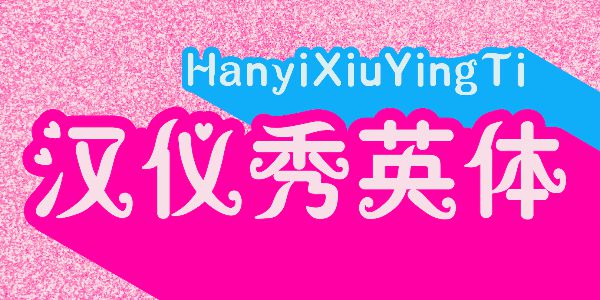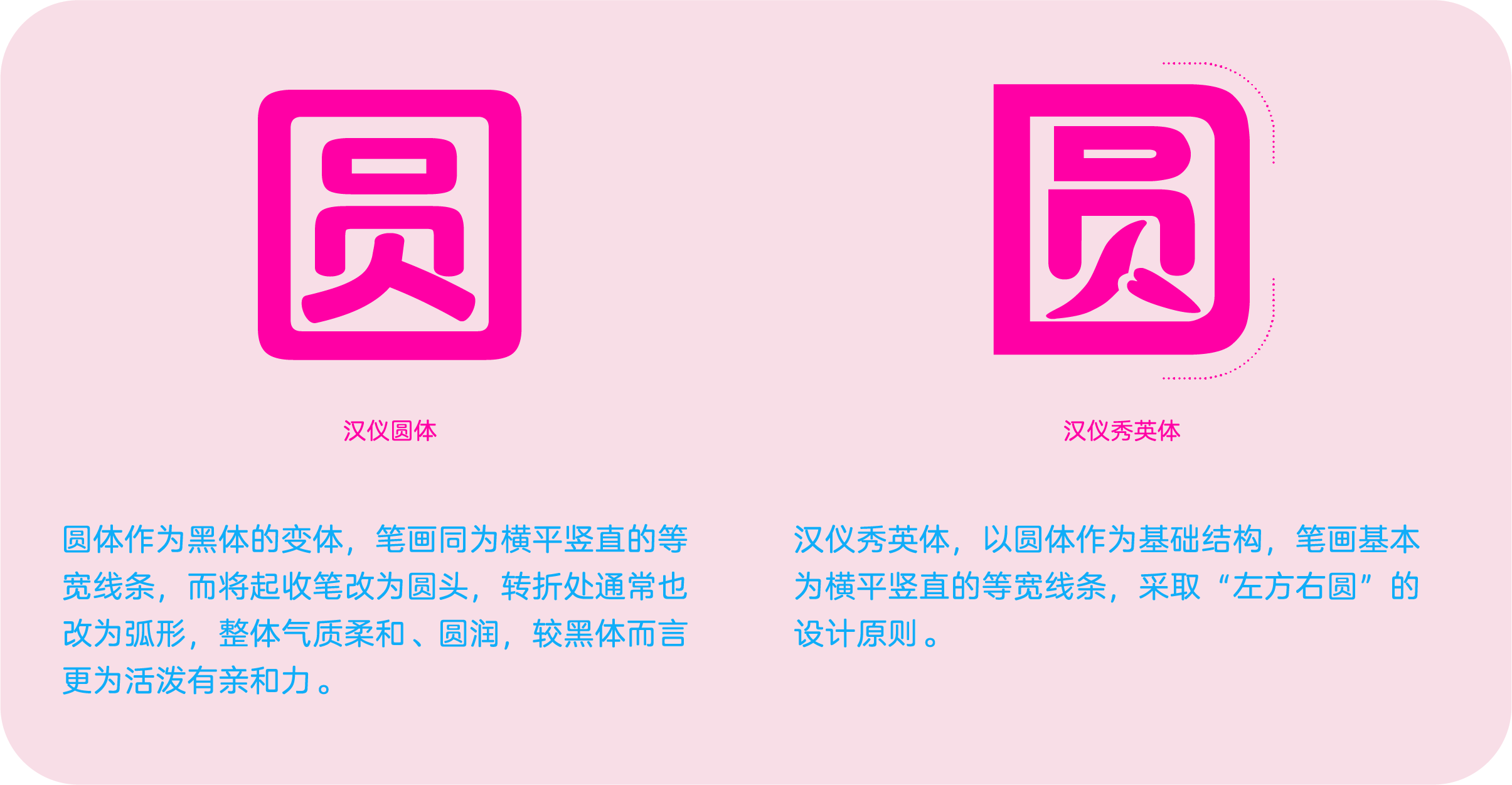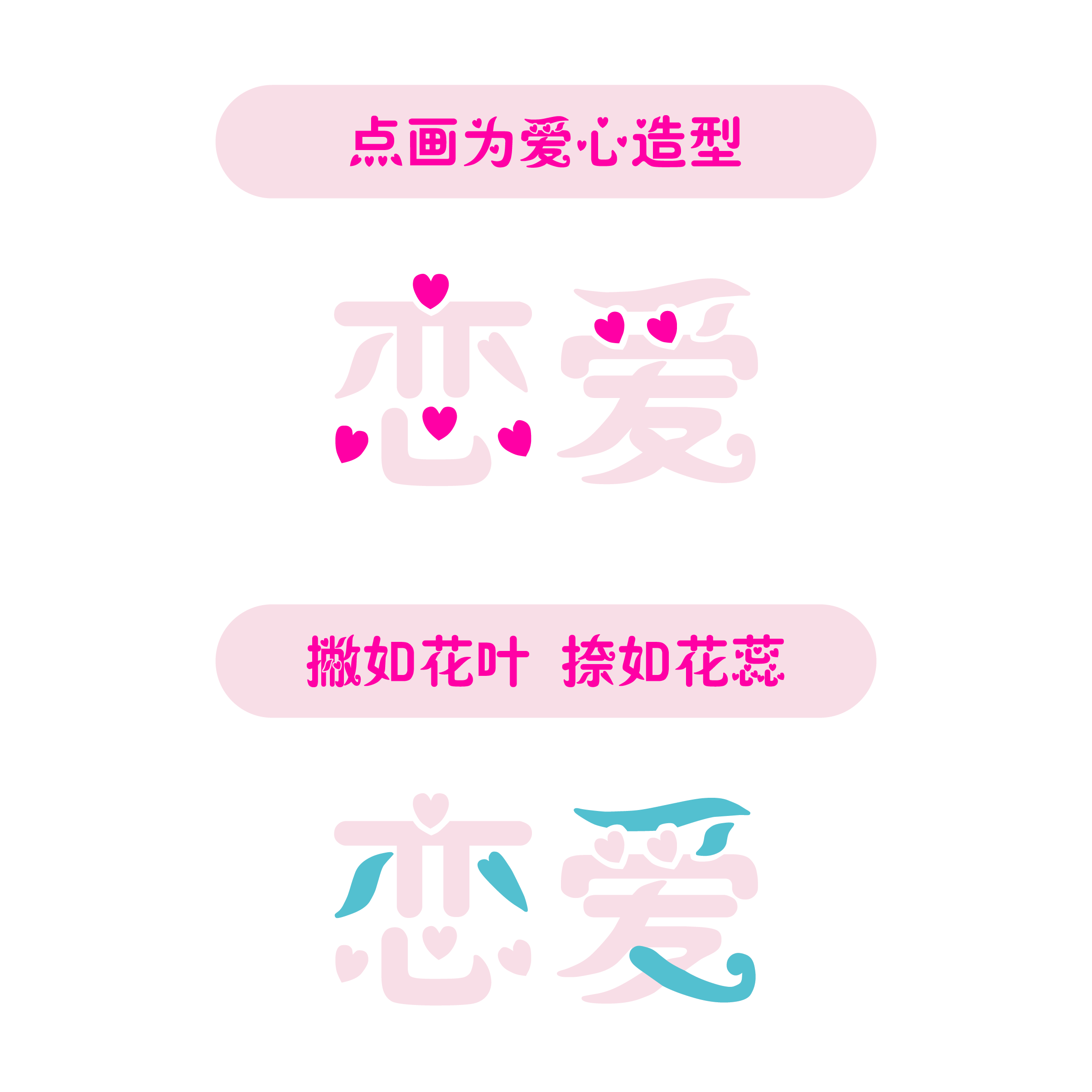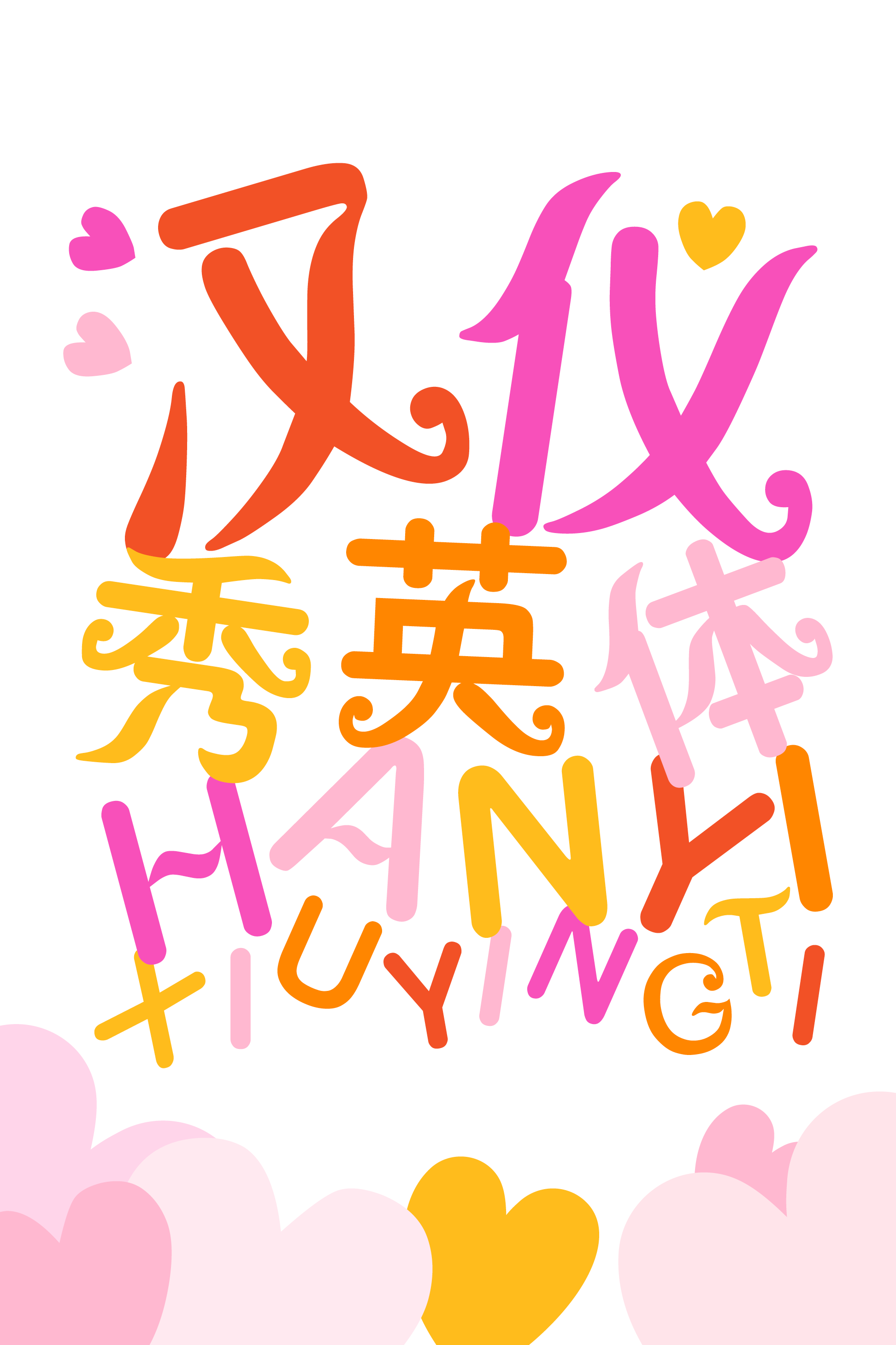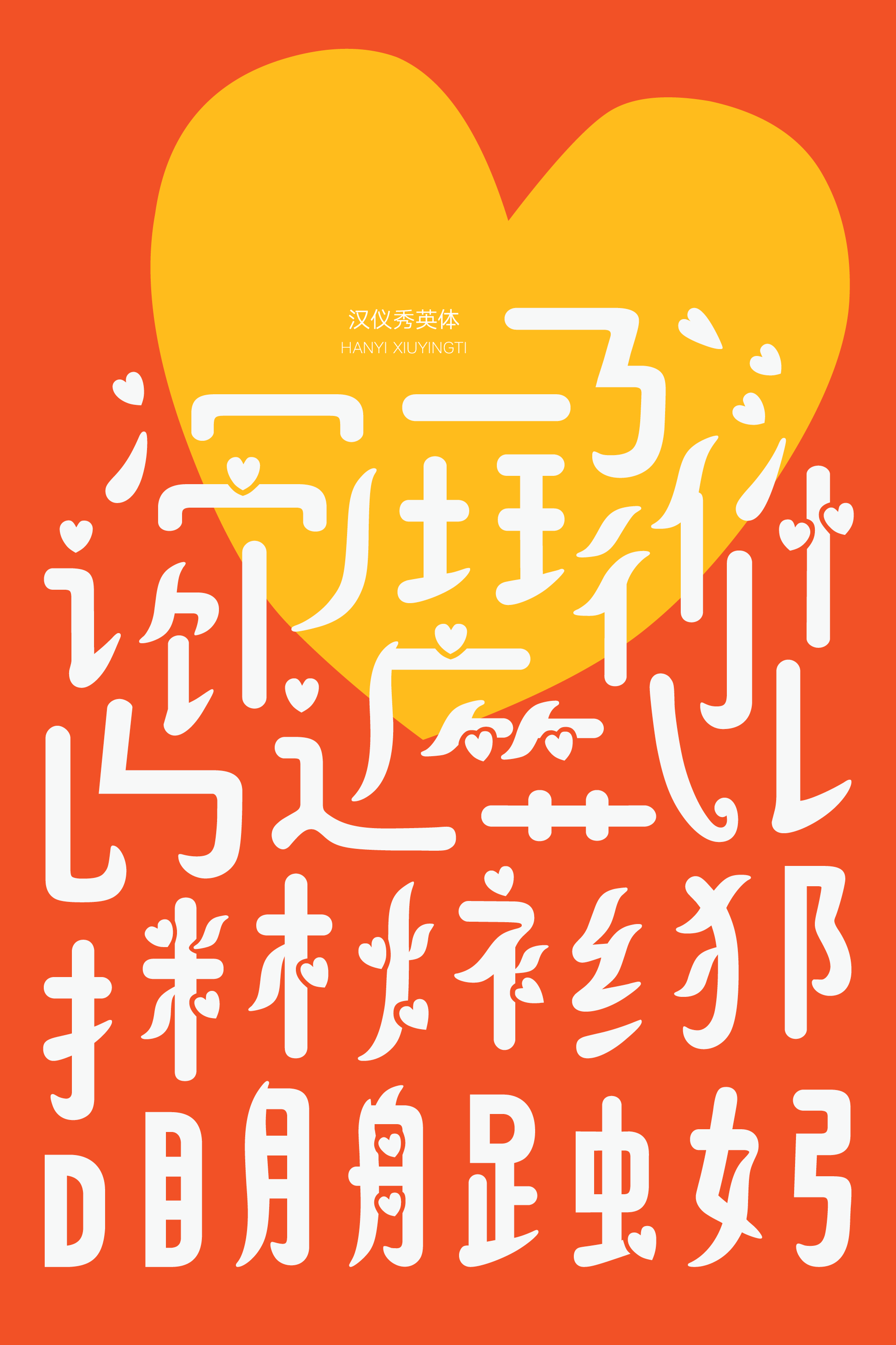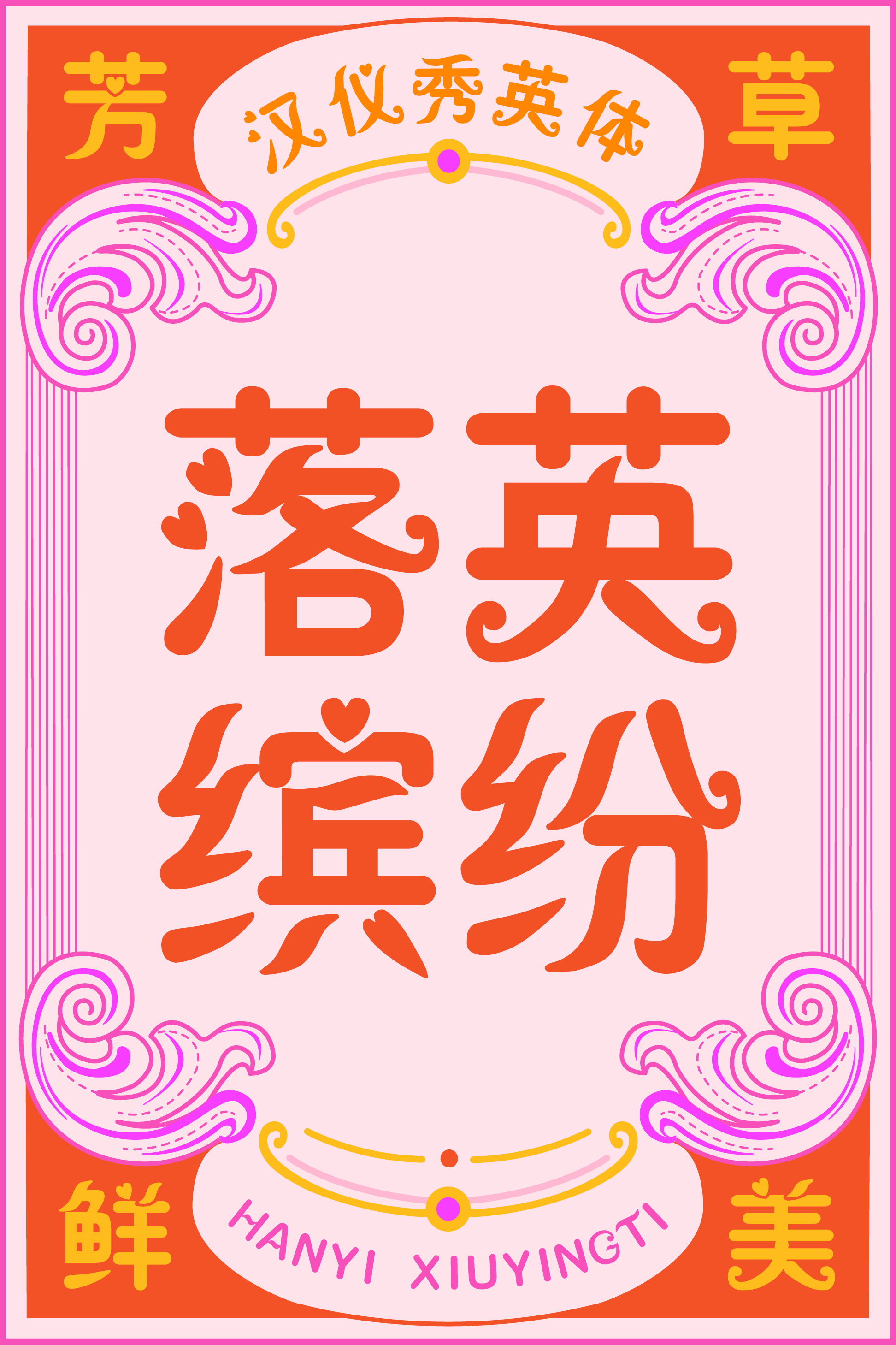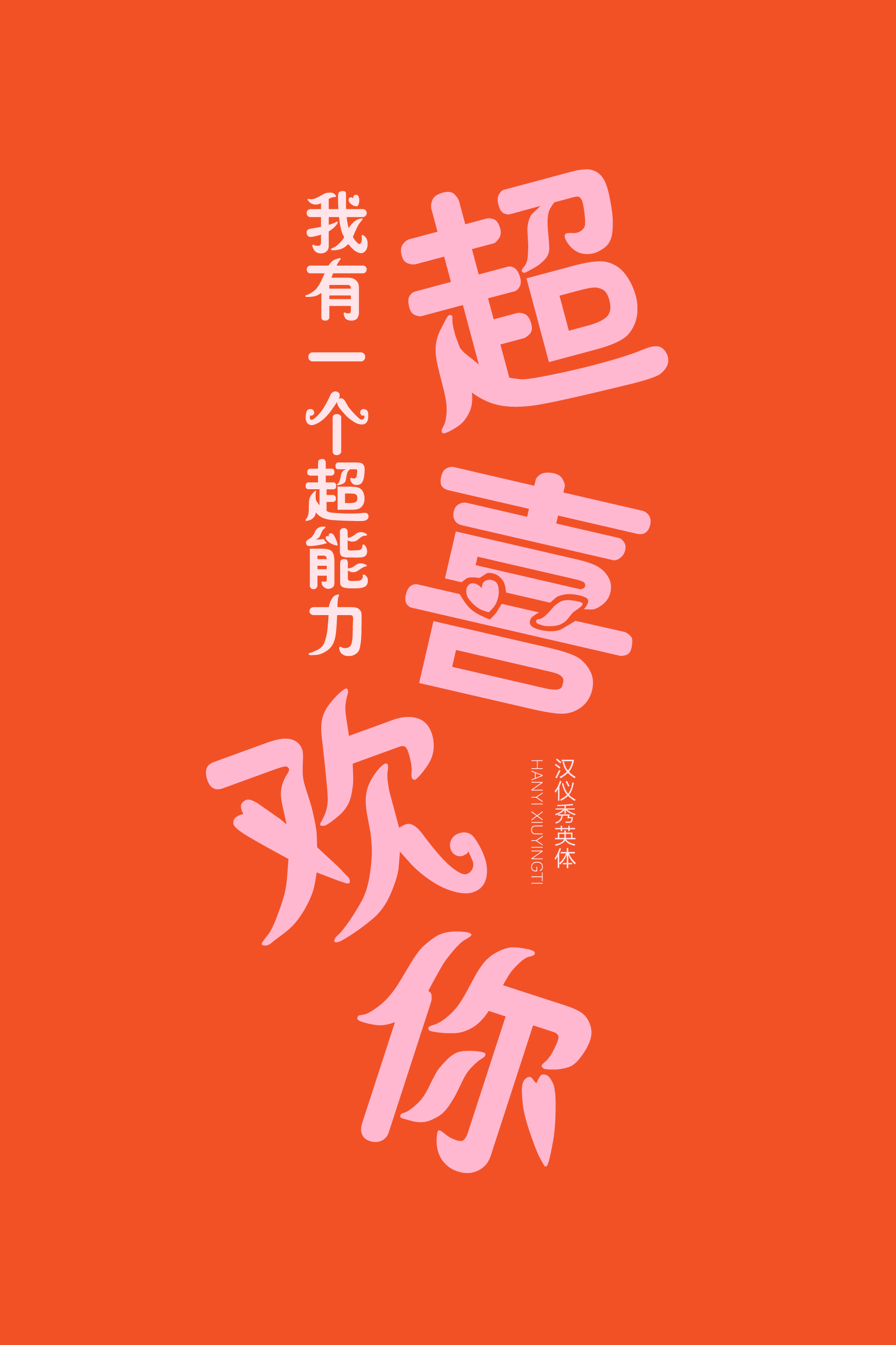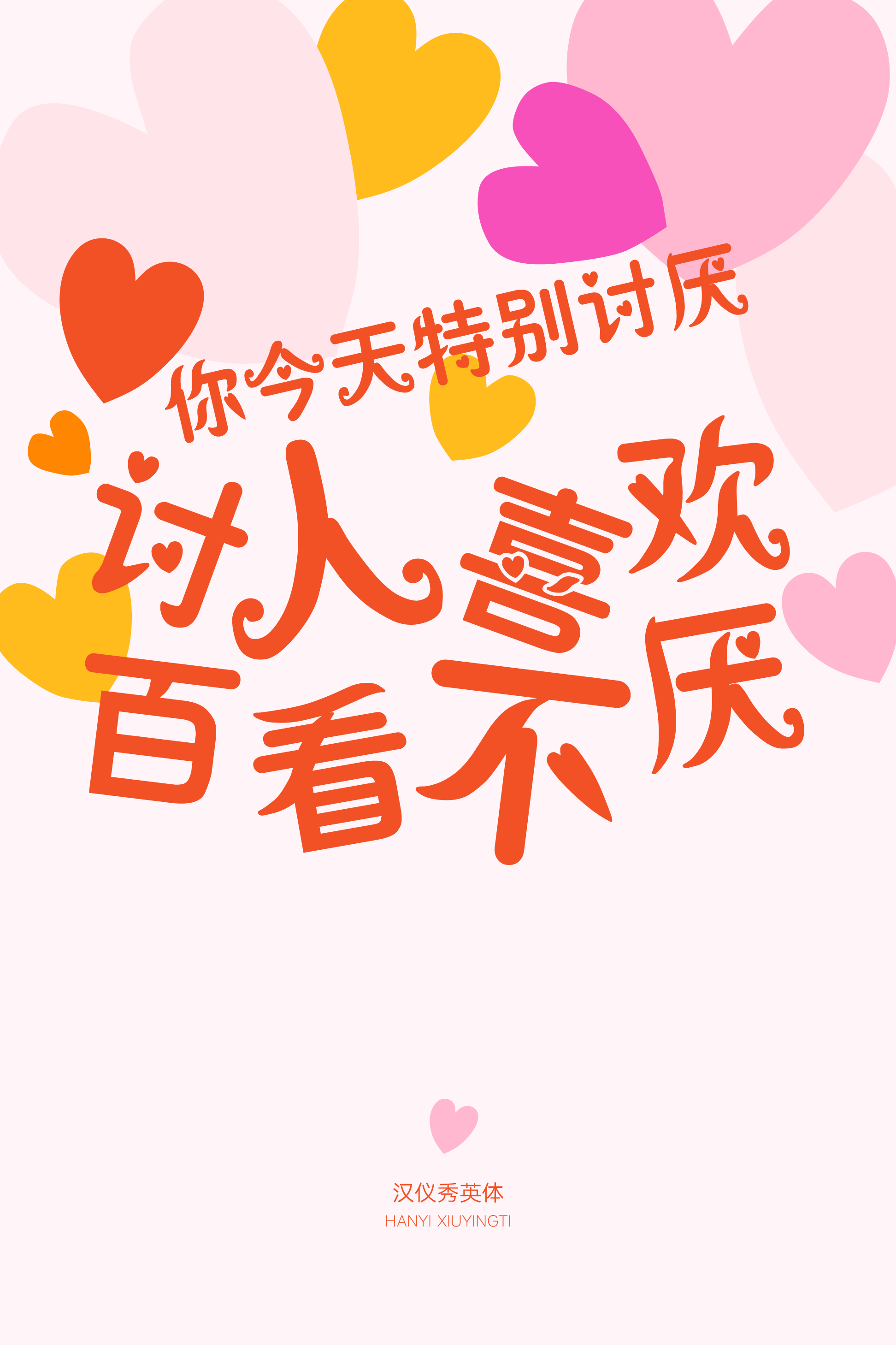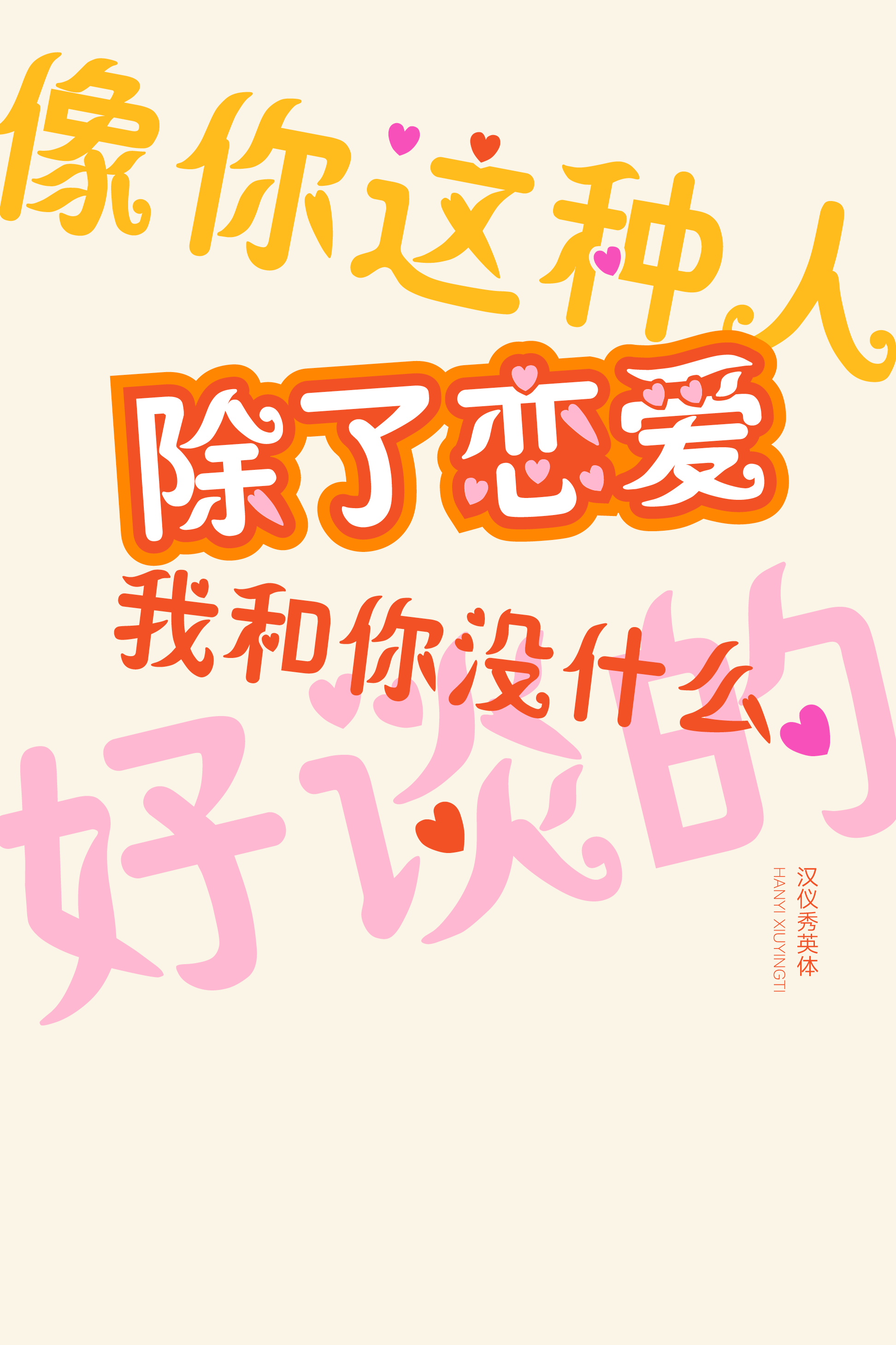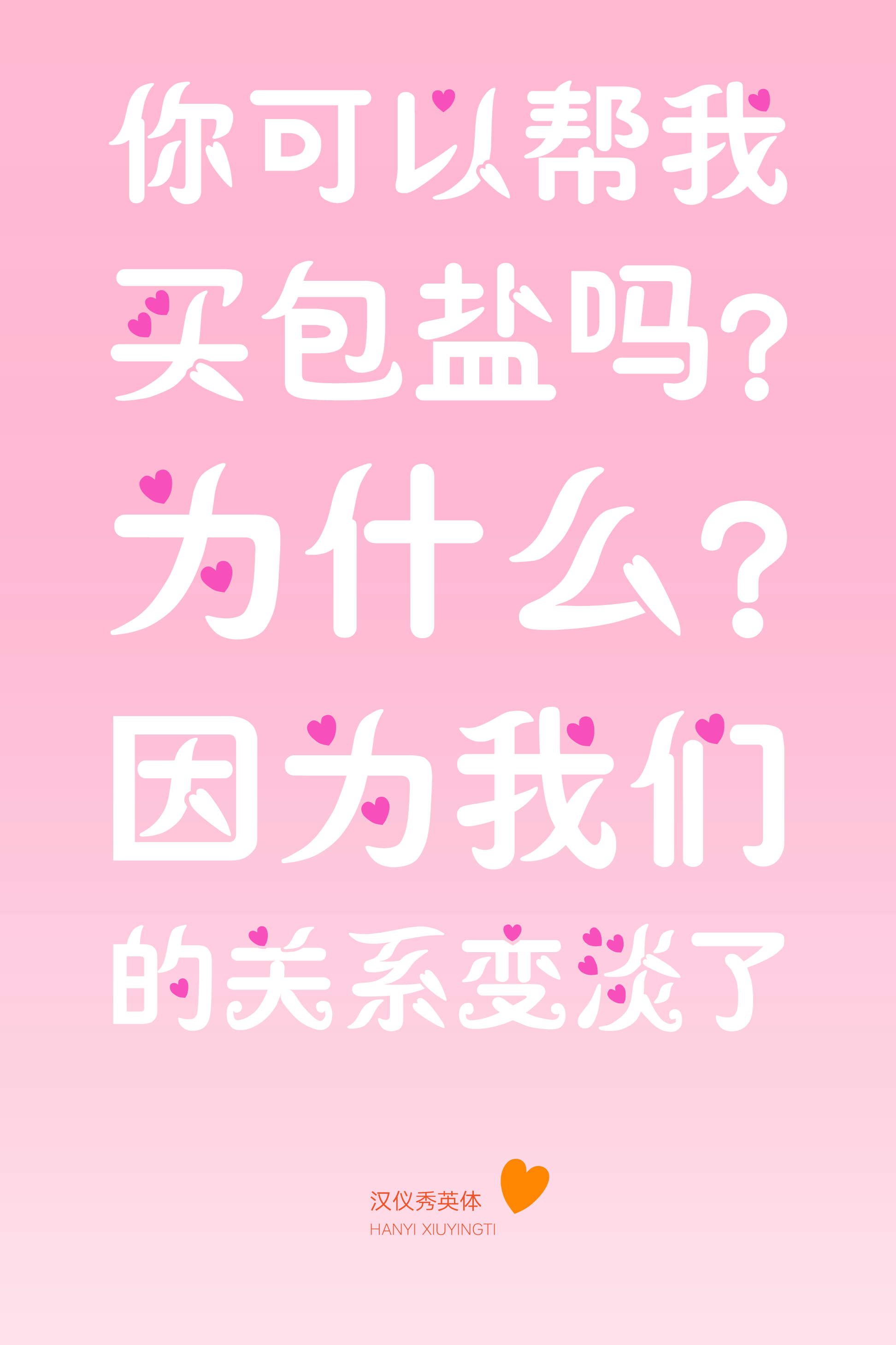
汉仪秀英体
诞生于世纪末的汉仪秀英体,由汉仪字库终身荣誉员工、国家级字体设计大师邹秀英设计。以颇具亲和力的圆体为基础结构,加入别出心裁的笔画设计:爱心造型的点画、撇如花叶、捺如花蕊。汉仪秀英体气质复古优雅,如同呢喃软语,书写千禧浪漫故事。
千禧年间的大街小巷,你一定曾与汉仪秀英体在某个转角相遇……
以圆体作为基础结构,有亲和力。
笔画设计简洁而别出心裁:
点画为爱心造型,长点似花瓣,撇如花叶飘动舒展,捺如花蕊微微蜷曲。
特殊造型的笔画搭接处留有空白,增添字体的呼吸感。
西文部分加入花叶、花蕊的曲线,中西文搭配书写满纸浪漫。